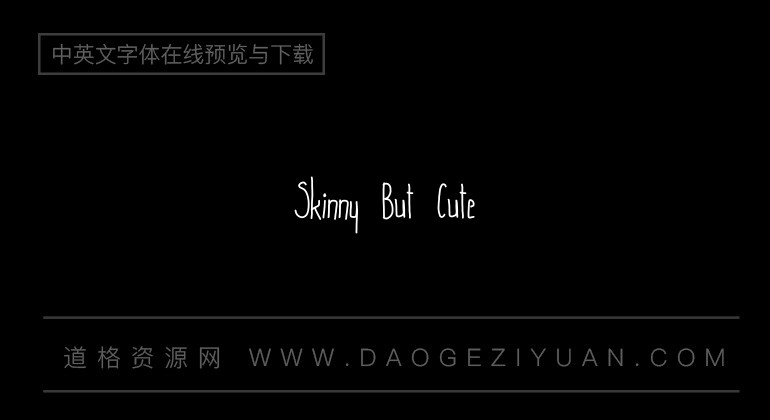
Skinny But Cute(瘦但可爱)是一种手写风格的字体,具有优美、简洁、艺术感和现代感。它的特点是线条细腻、轻盈、柔和、流畅,字形优美,字母间距恰到好处,整体看起来非常舒适和可爱。 Skinny But Cute 字体适合用于制作卡片、海报、品牌标识、商品包装、书籍封面、手写式标语、名片等设计项目,也可以用于个人日记、手账、信笺等文本排版。它是一种非常灵活的字体,可以适应不同的设计风格和场景,在许多方面都有广泛的应用。内容介绍
Skinny But Cute是一款非常不错的手写艺术字体,具有很好的视觉感,适合于文化类的宣传设计、商业类品牌的广告和产品包装设计以及个性化文字排版等较多场景。